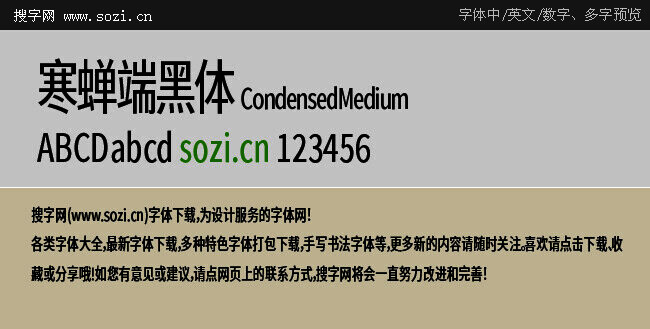
寒蟬端黑體CondensedMedium
搜字網(wǎng)給大家提供一款寒蟬端黑體CondensedMedium中文字體下載,寒蟬端黑體是基于思源黑體進行調整的黑體字體,在原字體風格上重新插值生成,Condensed系列的寒蟬端黑體是思源黑體的長體版本。適用于標題設計、海報設計、書籍排版以及網(wǎng)頁設計等應用。